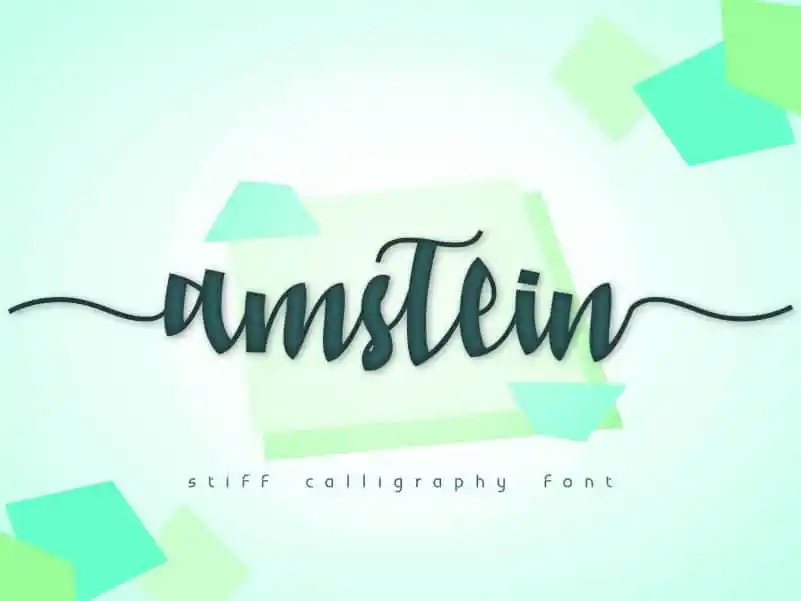
Amstein Script Font – Download Grátis
Amstein Script Font é uma elegante fonte escrita a mão que traz brilho e fluido movimento às letras. Seu equilíbrio perfeito entre beleza e proporções faz dela um recurso excepcional para qualquer projeto de design criativo, desde criações minimalistas até elementos gráficos mais elaborados. Com seu estilo elegante e suave, Amstein Script é uma escolha ideal para quando você precisa adicionar um toque único que brilha em seus projetos. Seja para etiquetas de produtos sofisticadas ou layouts de jornalismo visual, essa fonte oferece o ideal equilíbrio entre beleza e praticidade, tornando-a um complemento indispensável ao seu arsenal de recursos gráficos.
Designer: Nuryanto Dwi